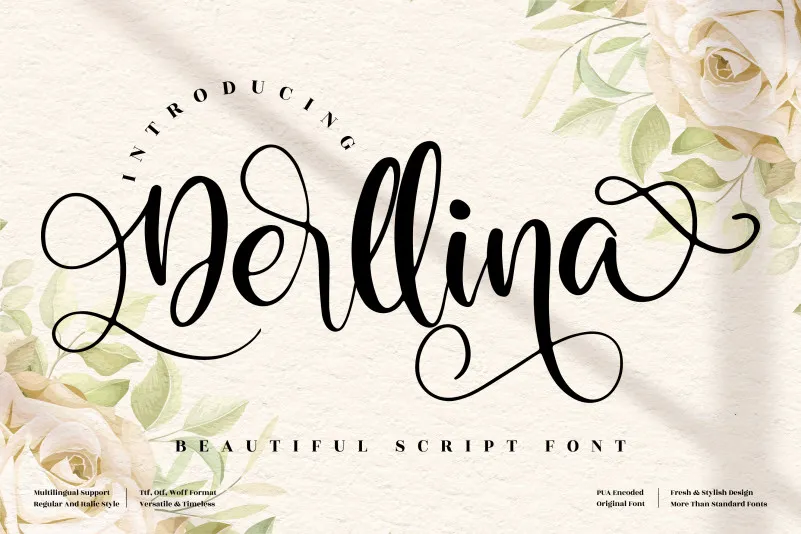
Derllina Font é uma elegante tipografia feita à mão que combina a frescura da escrita livremente com um toque único e impactoso. Esta fonte traz uma vibe de luxo, enriquecendo projetos gráficos que você deseja criar! Além disso, o fato de ser PUA (Proprietary Unicode Area) codificado significa que você pode acessar facilmente todos os incríveis gílios e ligaturas que ela possui. Derllina Font é mais do que uma fonte: é um recurso versátil para designers que buscam inovação em seus projetos. Esta font promete dar um toque distintivo a qualquer arte digital, tornando-a irresistivelmente chamativa e personalizável.